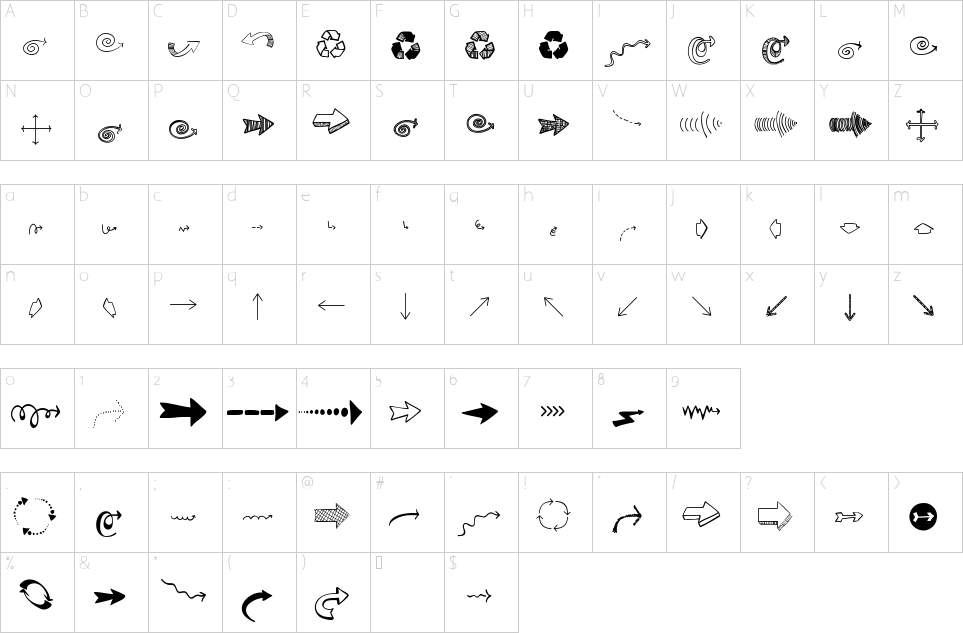
Austie Bost Arrow Mania Font – Download Grátis
Austie Bost Arrow Mania é uma fonte criada por Austie Bost Fonts que se destacou pela sua simplicidade e originalidade, tornando-se uma opção popular para designers e criadores de materiais digitais. Este fonte é ideal para quem busca uma solução elegante e moderna para seus projetos, especialmente em ambientes como sites, portais de notícias e aplicativos de comunicação. Com design minimalista e linhas leves, Arrow Mania oferece uma aparência agradável que se adaptará a vários estilos de design, desde o moderno e clean até o gráfico e expressivo. Com uma vasta aplicabilidade e um design intuitivo, Arrow Mania é uma escolha ótima para qualquer projeto que valorize a estética clara e a simplicidade. Se você está procurando por uma fonte para complementar seus designs em uma plataforma Windows ou Mac, Austie Bost Arrow Mania é a escolha perfeita.